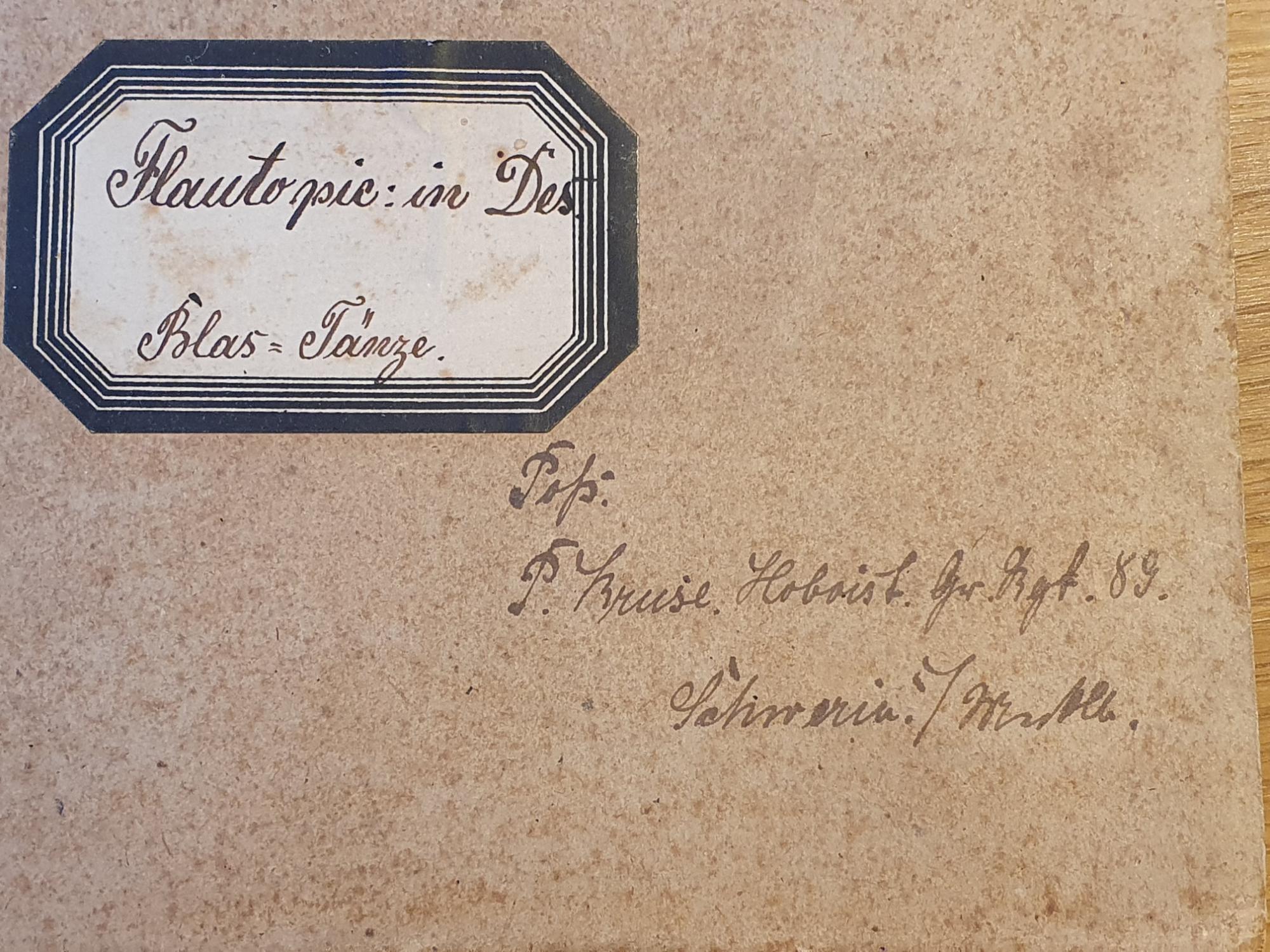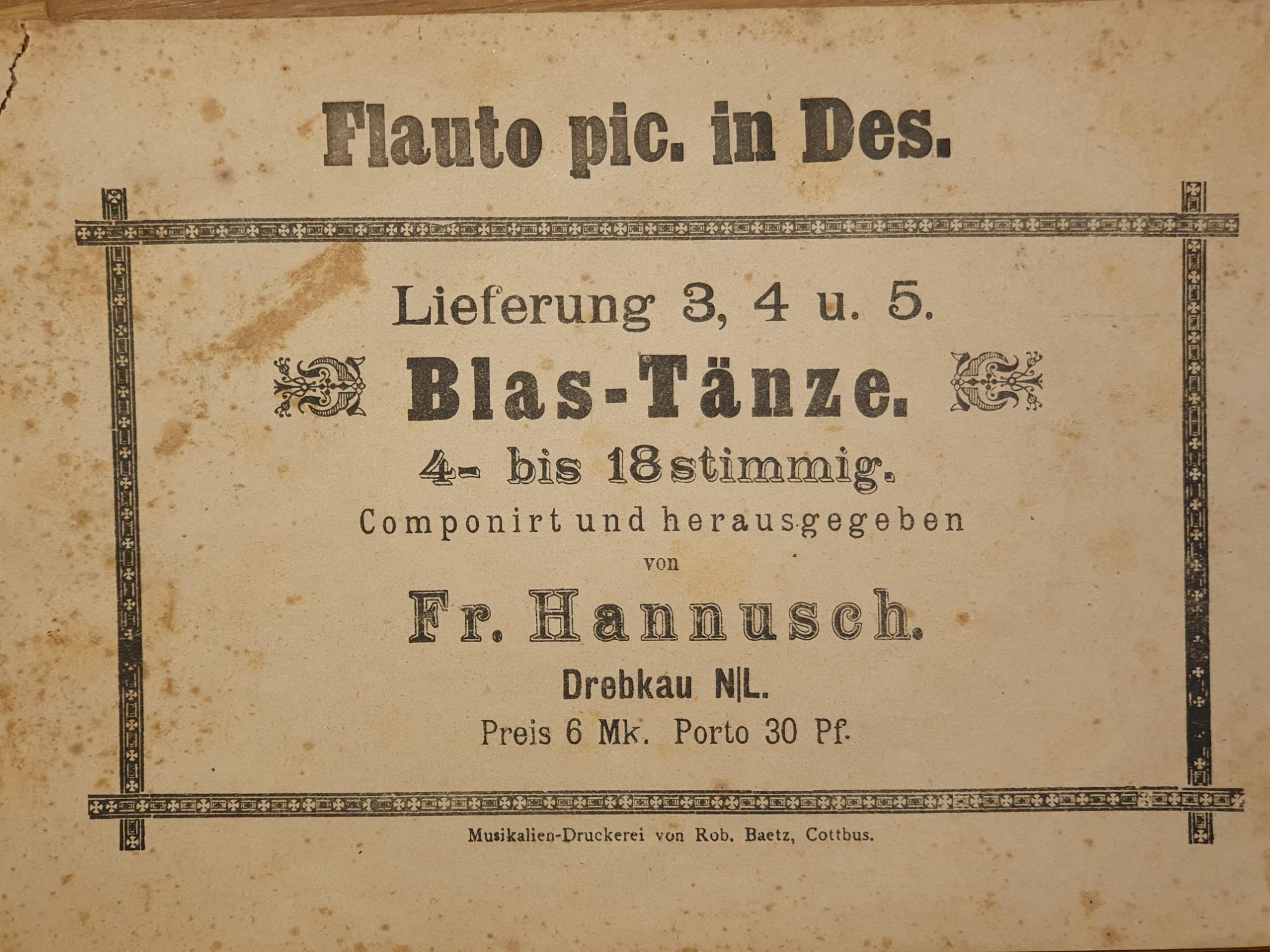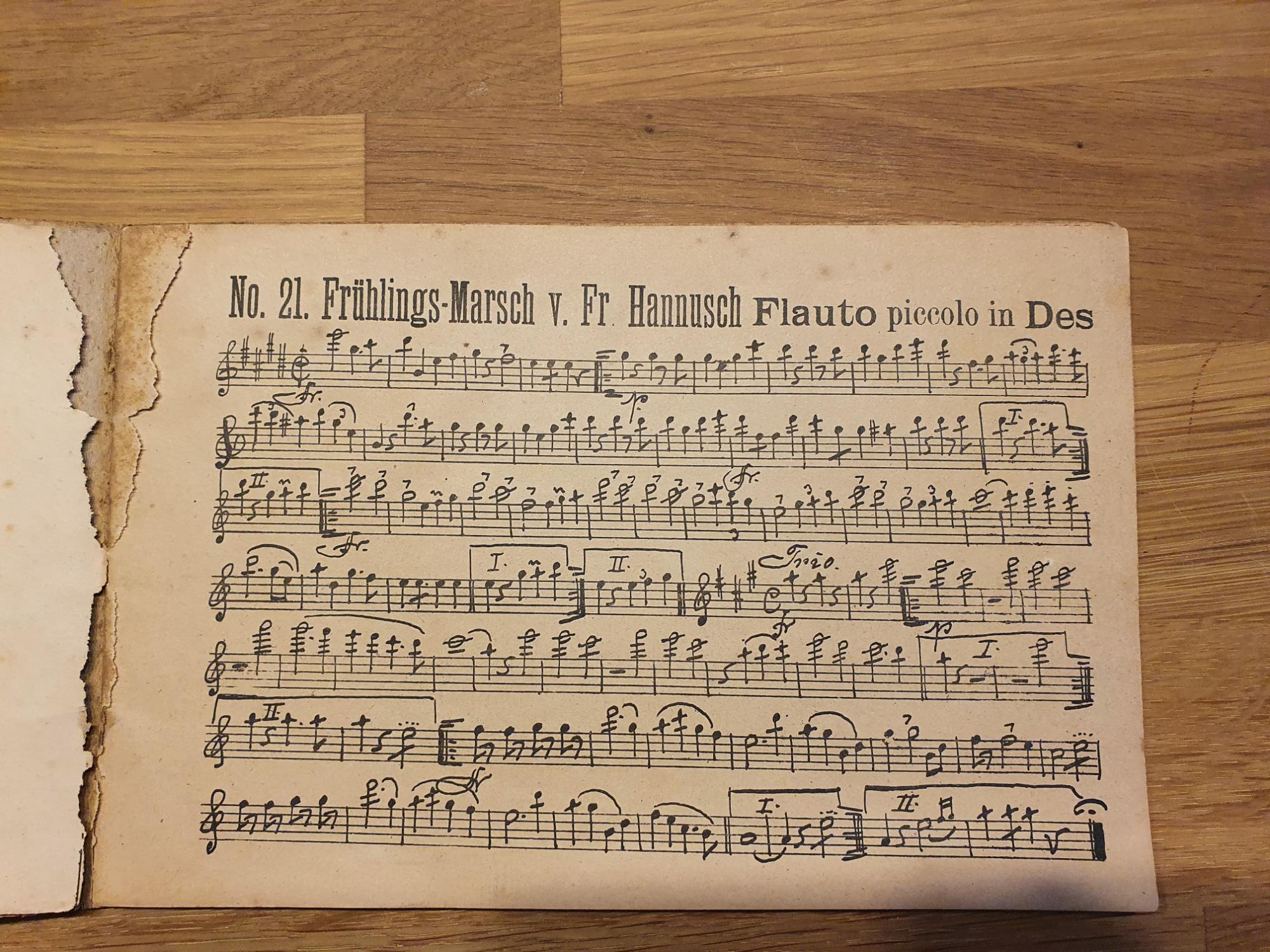
Wer kennt die Schrift und kann sie übersetzen? (Notenbuch)
ich hoffe, dass ich hier in diesem Forum an der richtigen Stelle bin. Ich habe in alten Unterlagen meiner Eltern ein altes Notenbuch ohne Jahresangabe gefunden. Dieses stammt aus der Musikalien-Druckerei Baetz, Cottbus, ist allerdings ohne jegliche Zeitangabe.  Der Aufkleber ist eindeutig zu identifieren. Auf dem Einband ist handschriftlich der Eintrag (siehe Anhang) notiert, den ich aber leider nicht entziffern kann. Vielleicht ist es eine Widmung oder eine Besitzkennung. Die 89 sagt mir auch nicht direkt etwas. Um das zeitlich in etwa einordnen zu können, bin ich für Hilfe dankbar.
Ein Hoboist ist jedenfalls ein Oboist … und »Schwerin/Mecklb.« fällt mir auch gleich ins Auge.
Flautopie: in Des.
Blas-Tänze.
Pohs:
P. Kruse. Hoboist. Gr. Rgt. 89.
Schwerin/Mecklb.
Na, da haben sich Fehler eingeschlichen.
Flauto pic[colo]
Poss[ession]
Ich habe zwischenzeitlich mal versucht, mehr über die Komposition herauszufinden: leider vergebens.
Für die oben bezeichnete Musikalien-Druckerei habe ich überhaupt nur einen Nachweis gefunden, der nicht weiterhalf. Über das Wort "Blas-Tänze" bin ich bei den offenbar zu ihrer Zeit weit verbreiteten und beliebten "Bismarker Blastänzen" von Wilhelm Lüdecke (1868–1938) gelandet. Dessen Werke (darunter eine Menge Militärmusik) sind aber anscheinend im Selbstverlag erschienen; eine Verbindung nach Cottbus habe ich nicht gefunden. Außerdem hätte ich nach der Aufmachung des Titelblatts vermutet, dass die Noten deutlich vor der Wende zum 20. Jh. erschienen sind; mich erinnern Schrift und Gestaltung eher an das frühe 19. Jh. Aber das kann täuschen.
Was ich herausgefunden habe, ist, dass "Hoboist" offenbar synonym für Bläser in einer Militärkapelle verwendet wurde; entsprechend werden die Militärkapellen auch als "Hoboistenkorps" bezeichnet (man findet z.B. Zeitungsausschnitte vom Ende des 19. Jh., wo dokumentiert wird, dass das "Hoboistenkorps" des von Bernd identifizierten Regiments 89 bei Abendveranstaltungen in Schwerin gespielt hat).
Mit anderen Worten: eine Menge "sinnloser" Infos, die für die zeitliche Einordnung nicht wirklich weiterhelfen. :-(
Vielleicht liefert uns der Threadersteller noch die erste Seite der Noten.
Vielen Dank für die tollen Ausführungen und Hinweise! Jetzt kann ich das Notenheft jedenfalls in einen Kontext stellen, auch wenn eine konkrete zeitliche Einordnung wohl nicht möglich ist. Ich nehme die Anregung von HenningH gerne auf und stelle noch 2 Fotos dazu. Wie die handgeschriebenen Noten letztendlich vervielfältigt wurden, ist mir weiterhin unklar.
Wie die handgeschriebenen Noten letztendlich vervielfältigt wurden ...
Lithografie (Steindruck)?
Mit dem Namen des Komponisten, Fr[itz] Hannusch, kommt man ein wenig weiter: Ich habe zwar auf die Schnelle keine Lebensdaten gefunden; aber einschlägige Verzeichnisse weisen in den 1890er Jahren zahlreiche seiner Werke als gerade neu erschienen aus, etwa die Musikalisch-literarischen Monatshefte oder das Handbuch der musikalischen Literatur. Ich gehe also davon aus, dass die Blas-Tänze auch ungefähr in diese Zeit fallen (obwohl ich keinen direkten Hinweis darauf gefunden habe). Die Werke sind offenbar alle im Eigenverlag erschienen.
Ich nehme an, die Abbildung auf der Titelseite für die Bass-Stimme zeigt den Komponisten selbst. Was mich ein wenig verwirrt: Die Bass-Stimme verzeichnet unten die Lithographische* Anstalt Benicke, Leipzig, als Druckerei; die Trompeten-Stimme hat einen Hinweis auf Robert Baetz, Cottbus. Wurden die verschiedenen Orchesterstimmen an unterschiedlichen Orten gedruckt?
* Der Name der Druckerei bestätigt wohl Norberts Vermutung, dass solche Sachen als Lithographie gedruckt wurden, dass also die handgeschriebenen Noten auf den Lithographiestein übertragen wurden, von dem dann gedruckt wurde.